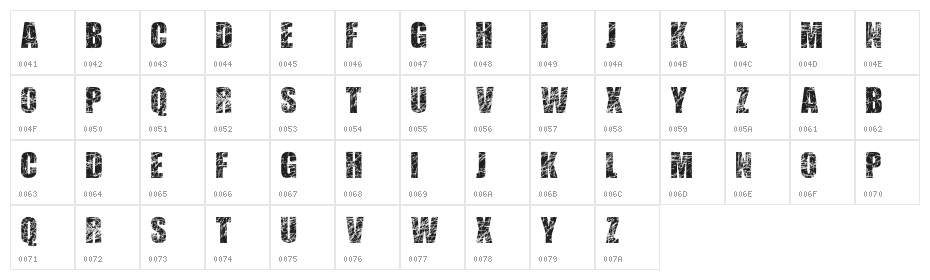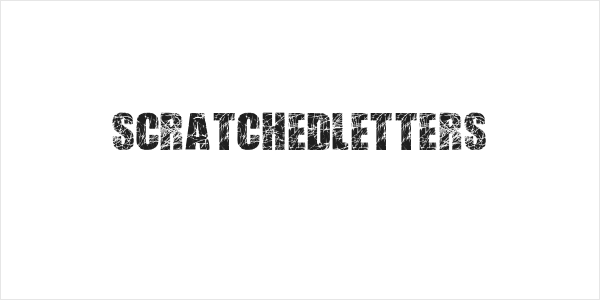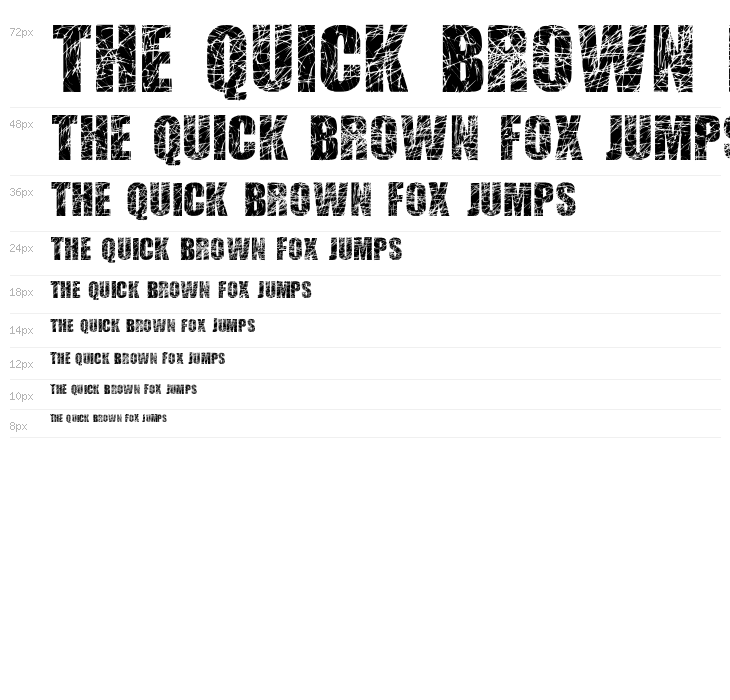
ScratchedLetters Font
✎ Distorted Eroded
| Proiecte propuse | Ideal for album covers, posters, streetwear branding, and any design needing a rugged, urban feel. |